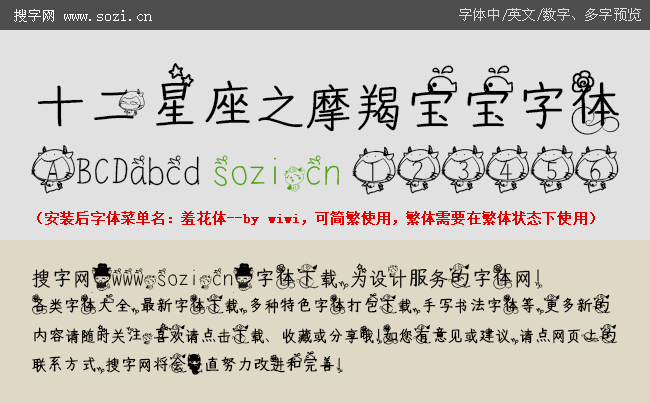
十二星座之摩羯寶寶字體
搜字網(wǎng)給大家提供一款很卡通的手機(jī)中文字體下載。修改者將它命名為十二星座之摩羯寶寶字體,這款手機(jī)字體是仿照兒童手寫風(fēng)格的卡通手寫字體,結(jié)構(gòu)帶有POP字體風(fēng)格,字體間還配上了非常有趣的卡通星座圖案,特別適合喜歡手機(jī)字體個(gè)性一些的朋友在手機(jī)上安裝使用。